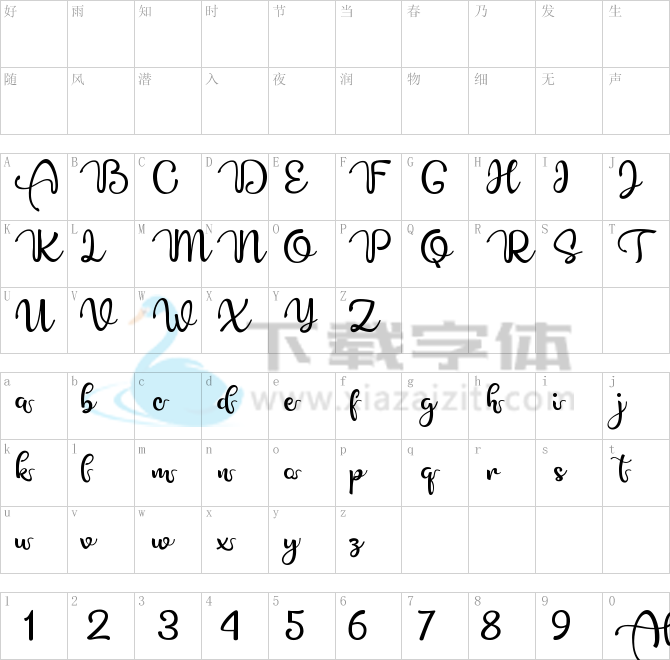
Aldania.otf字体下载,这款字体结构工整、笔画清晰,兼顾美观与易读性,适用于标题、正文、海报、包装、LOGO 等多种场景。字形优雅稳定,风格百搭耐看,适配日常排版与创意设计,让文字呈现更舒适、更具质感。Aldania.otf字体下载一笔一画,皆是细节,以均衡的比例、流畅的线条打造舒适视觉体验,字形端正大气,风格简约现代。无论是商业设计、品牌宣传还是日常排版,都能轻松驾驭,让文字更有格调与力量。Aldania.otf字体下载字体下载。